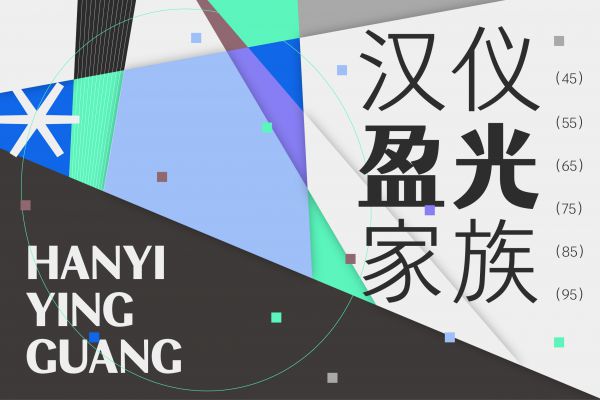
汉仪盈光 75U
一套现代简约的创意黑体家族字体,共包含6个字重。融合宋体的精致结构和黑体的现代感笔画,弧度自然流畅,轻柔简洁富有韧性。字内空间均匀,有呼吸感,部分笔画做减省处理。细款轻盈灵动,粗款新锐现代,整体中性气质刚柔得当,满足不同视觉层级的排版需求,适合用于标志广告、文化艺术、文博文旅、中高端商业品牌等使用场景。